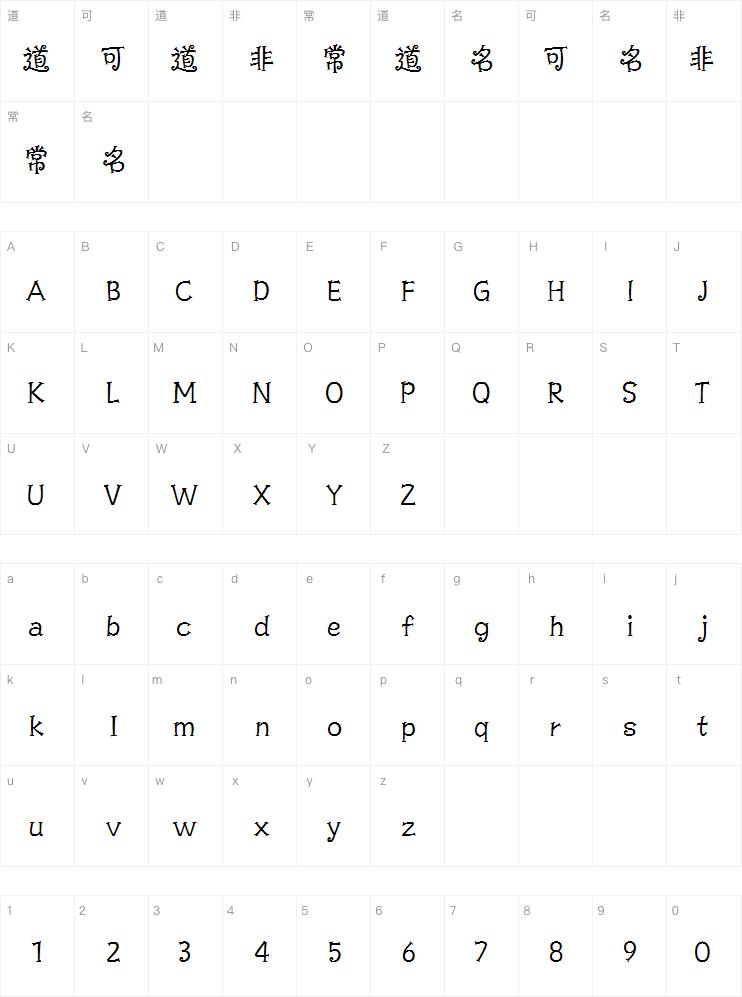
山海魔法精灵,是一款全新的字体,包含汉字9169个,符号200+个。该字体是一款卡通风哥特字体,该字体融合了西方哥特元素,字体独特,新颖华丽。这款字体有着很强的装饰性和醒目的视觉效果,字体结构空间均衡、字形灵动多变,童趣可爱,同时融入喇叭头起头和结尾,装饰性十足,带给人魔幻、卡通的视觉感受。撇和捺作为字形中延展性最高的两个笔画,形态灵动。整体活泼清新,造型生动有趣,具有灵活的适用性,天真俏皮又不失时尚感。在体现哥特风格的同时呼应了中文的笔画特征,并在设计上有意改善传统哥特体复杂难辨认的特性,尽量做到易辩、易读,保证了字体的实用性。汉字艺术与西方文字的融合,如精灵国度般华丽灵动,又宛如梵高的《星月夜》般神秘梦幻;个性鲜明的字体特征,散发着自由而俏皮的气息。在华丽而不失婉约中,感受哥特风的魅力。